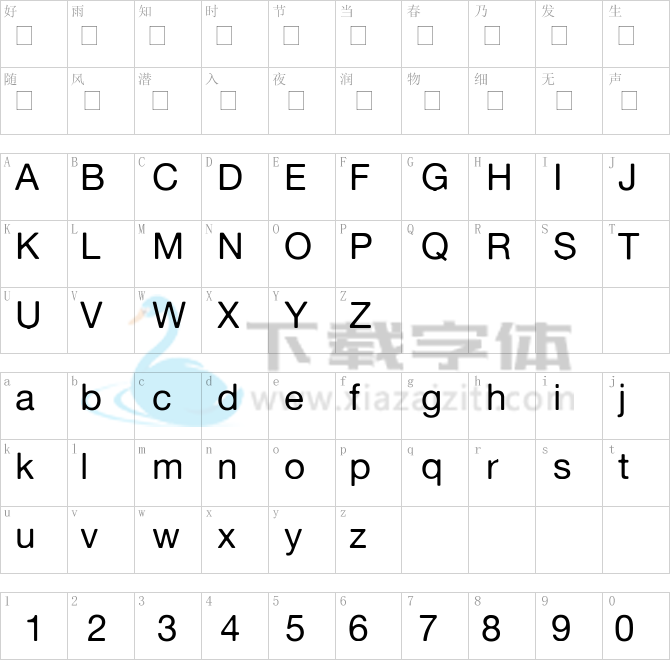
Alte Haas Grotesk.ttf字体下载,这款字体结构工整、笔画清晰,兼顾美观与易读性,适用于标题、正文、海报、包装、LOGO 等多种场景。字形优雅稳定,风格百搭耐看,适配日常排版与创意设计,让文字呈现更舒适、更具质感。Alte Haas Grotesk.ttf字体下载一笔一画,皆是细节,以均衡的比例、流畅的线条打造舒适视觉体验,字形端正大气,风格简约现代。无论是商业设计、品牌宣传还是日常排版,都能轻松驾驭,让文字更有格调与力量。Alte Haas Grotesk.ttf字体下载字体下载。